Auszeichnungsschriften
Typografischer Terminus für familiäre und extrafamiliäre Schriftschnitte (Schriftstile) in unterschiedlichen Schriftbreiten, Schriftlagen und Schriftstärken, die für Schriftauszeichnungen im »Gemischten Satz« neben der Grundschrift verwendet werden.
Etymologisch rührt der Begriff »Auszeichnung« aus der Inkunabelzeit der Jahre 1450 bis 1500. Denn Initialen, Rubriken, Lombarden, Illuminationen, Unterstreichungen, Auszeichnungsstriche sowie farbiger Schriftwechsel konnten in der Prototypografie technisch bedingt nur von Kalligraphen, Illuminatoren und Rubrikatoren händisch »ausgezeichnet« werden.
Auszeichnungsschriften werden – immer ausgehend von der Grundschrift – in leise und laute Auszeichnungsschriftschnitte unterteilt. Zu den leisen Auszeichnungsschriftschnitten zählen strichgleiche Schriftstile (siehe Schriftstärke), also beispielsweise der kursive Schriftschnitt oder die Kapitälchen innerhalb einer Schriftfamilie, zu den lauten Auszeichnungsschriftschnitten familiäre oder extrafamiliäre fettere Schriftstile, beispielsweise halbfette oder fette Schriftschnitte.
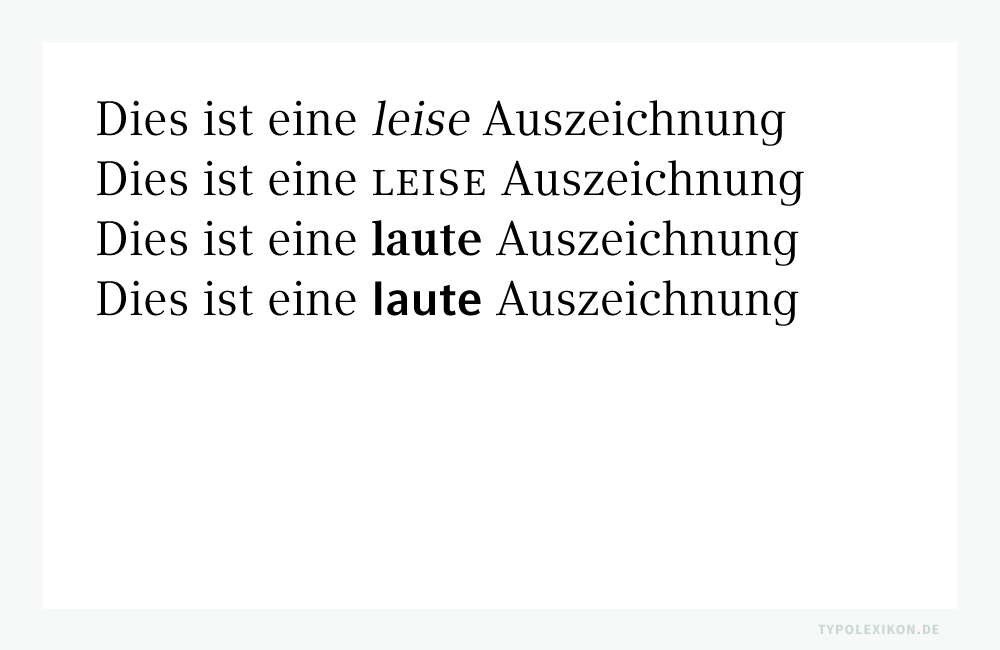
Auszeichnungen und Auszeichnungsschriften werden aufgrund einer semantisch-typografischen Auszeichnungsmatrix (siehe Schriftmischung) fixiert. Die semantische Gliederung gehört in den Bereich Text/Redaktion, die Verknüpfung der Semantik mit einer Schriftstilvariante gehört in den Bereich der Makrotypografie und die Wahl einer bestimmten Schriftart in das Segment der Mikrotypografie.
Im materiellen Schriftsatz (z.B. Bleisatz) wird traditionell – ausgehend vom normalen Schriftschnitt – der kursive, halbfette und fette Schriftschnitt sowie die Kapitälchen innerhalb einer Schriftfamilie als »Auszeichnungsschnitte« bezeichnet.